4つのウェイトをそろえた使いやすいセリフ書体:JANSON
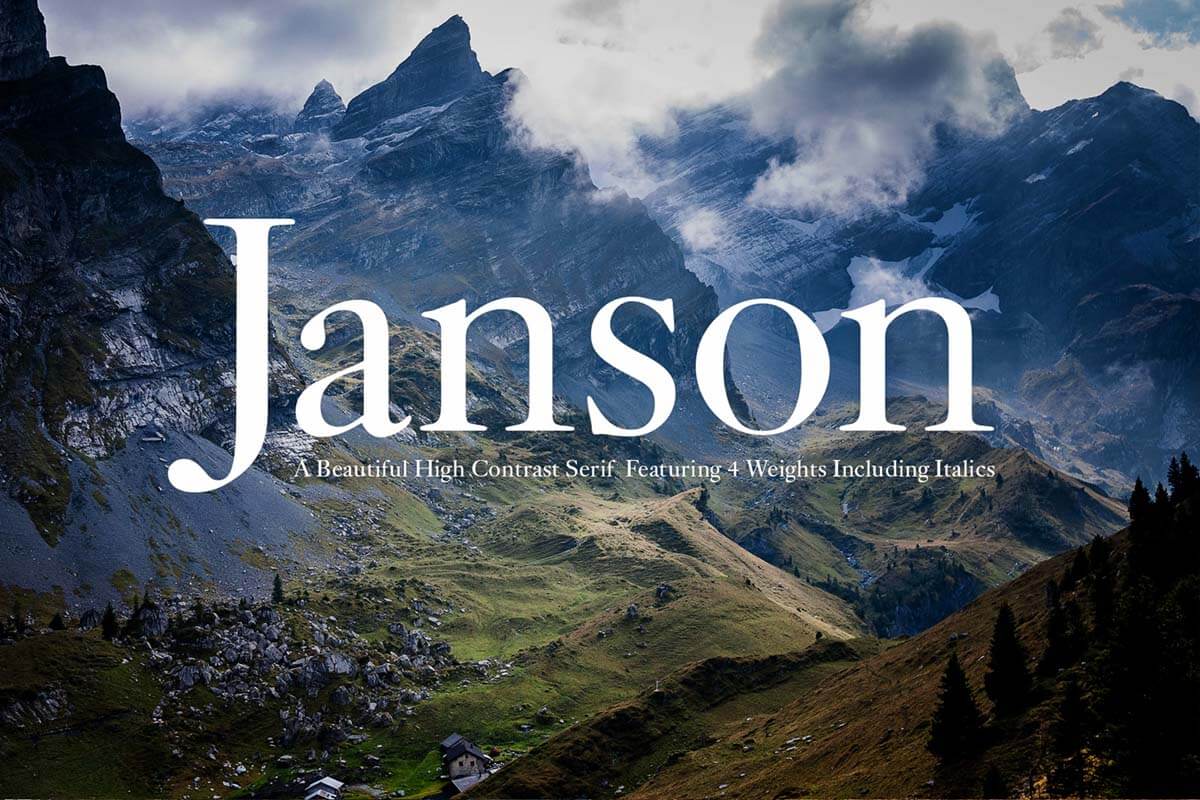
9バージョンを収録したシンプルなセリフフォント。スモールキャプスもあります。
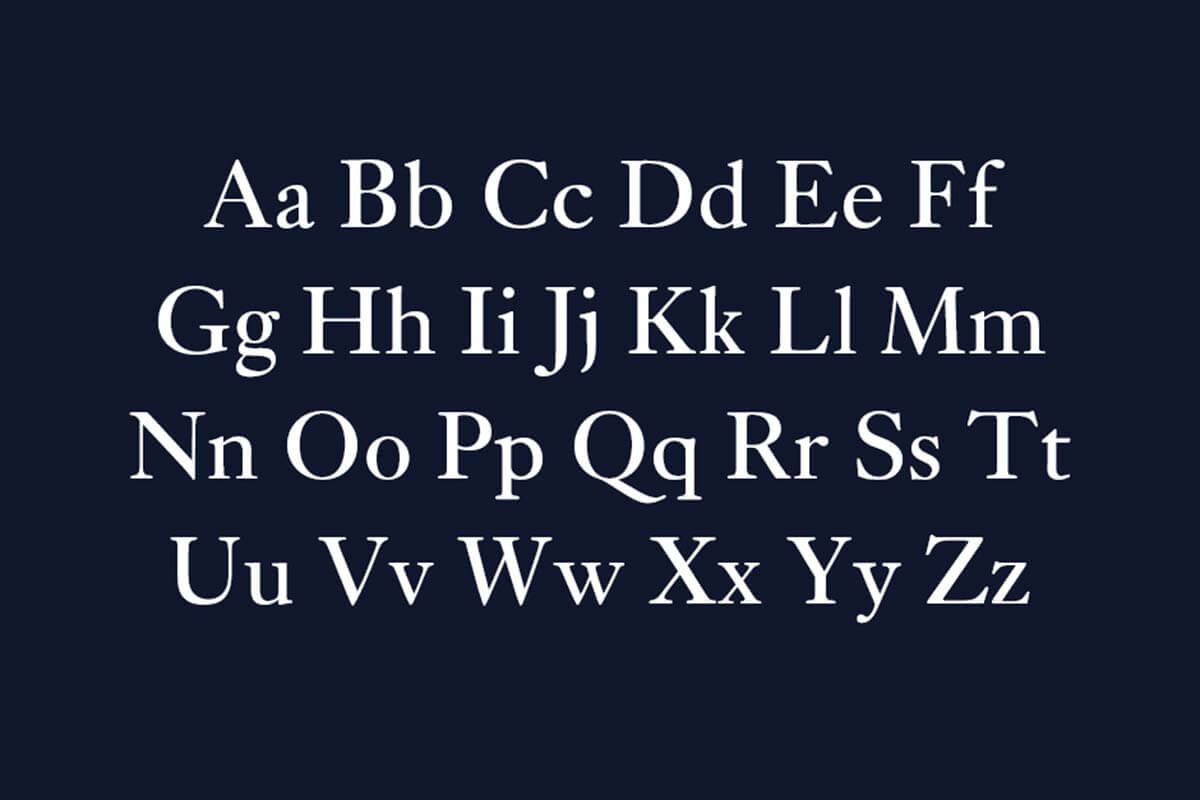
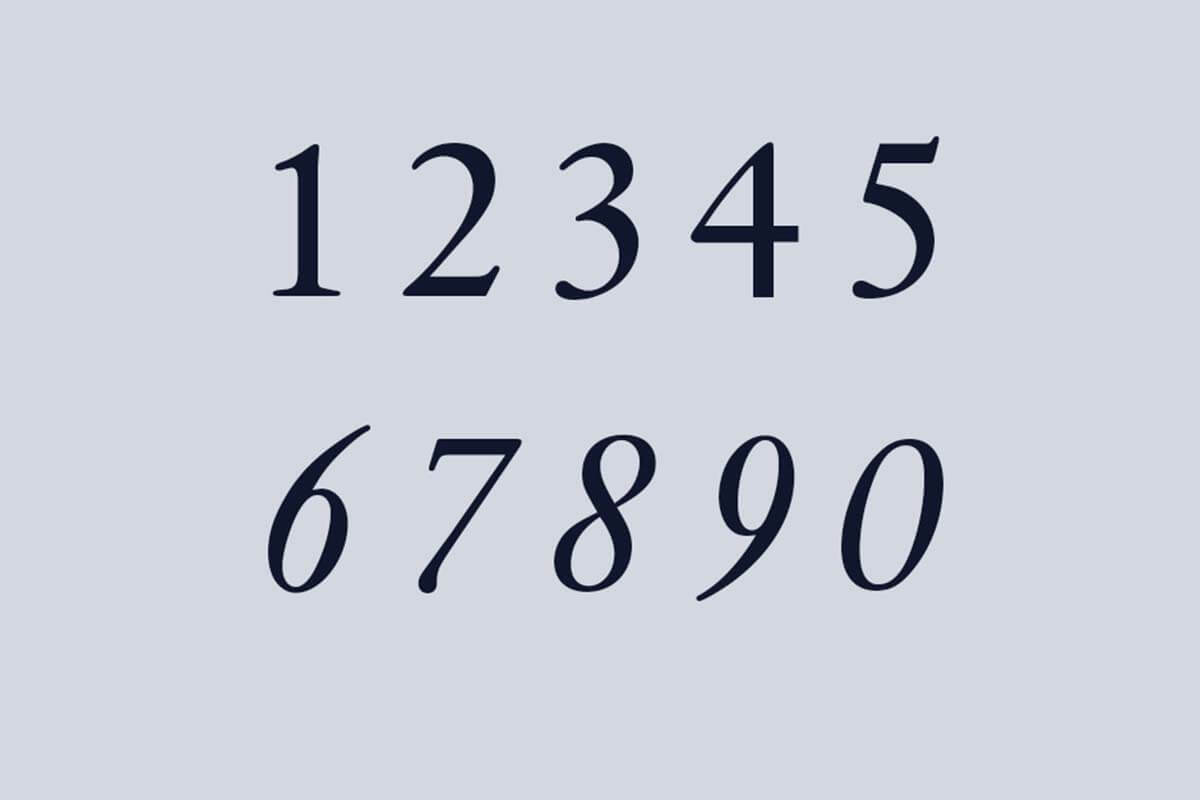
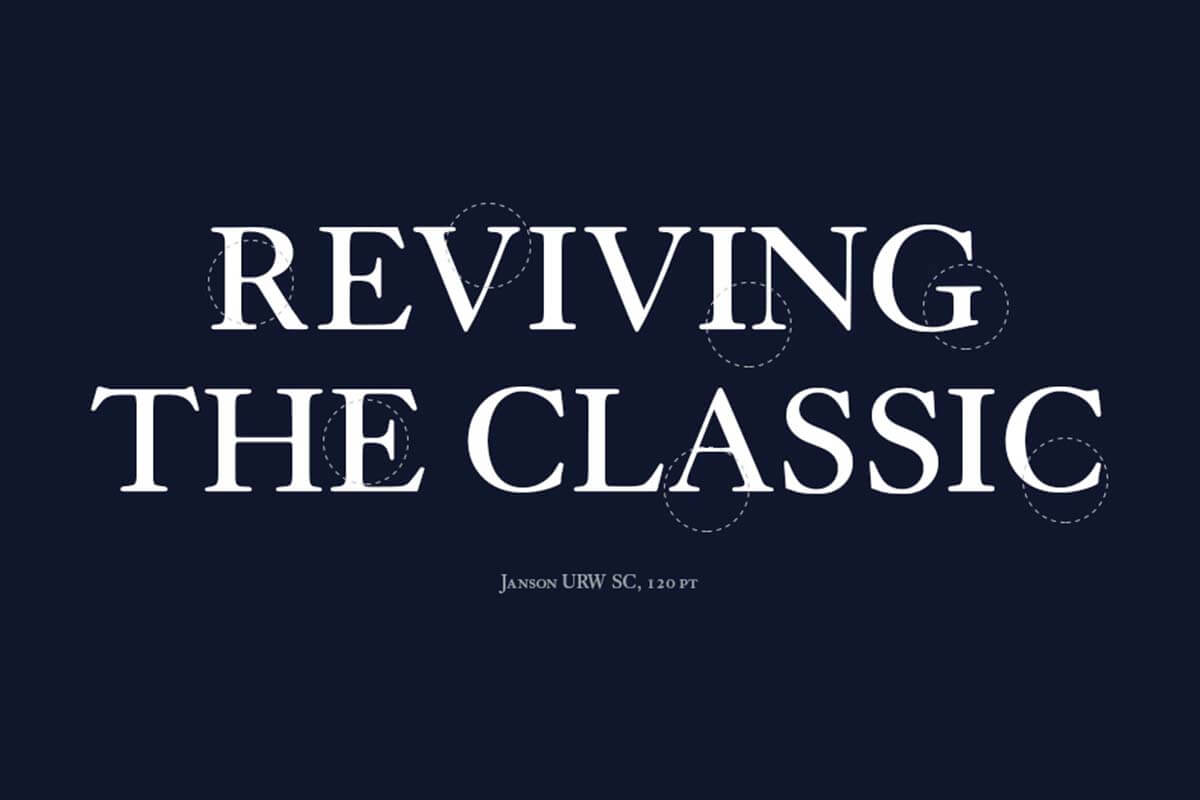
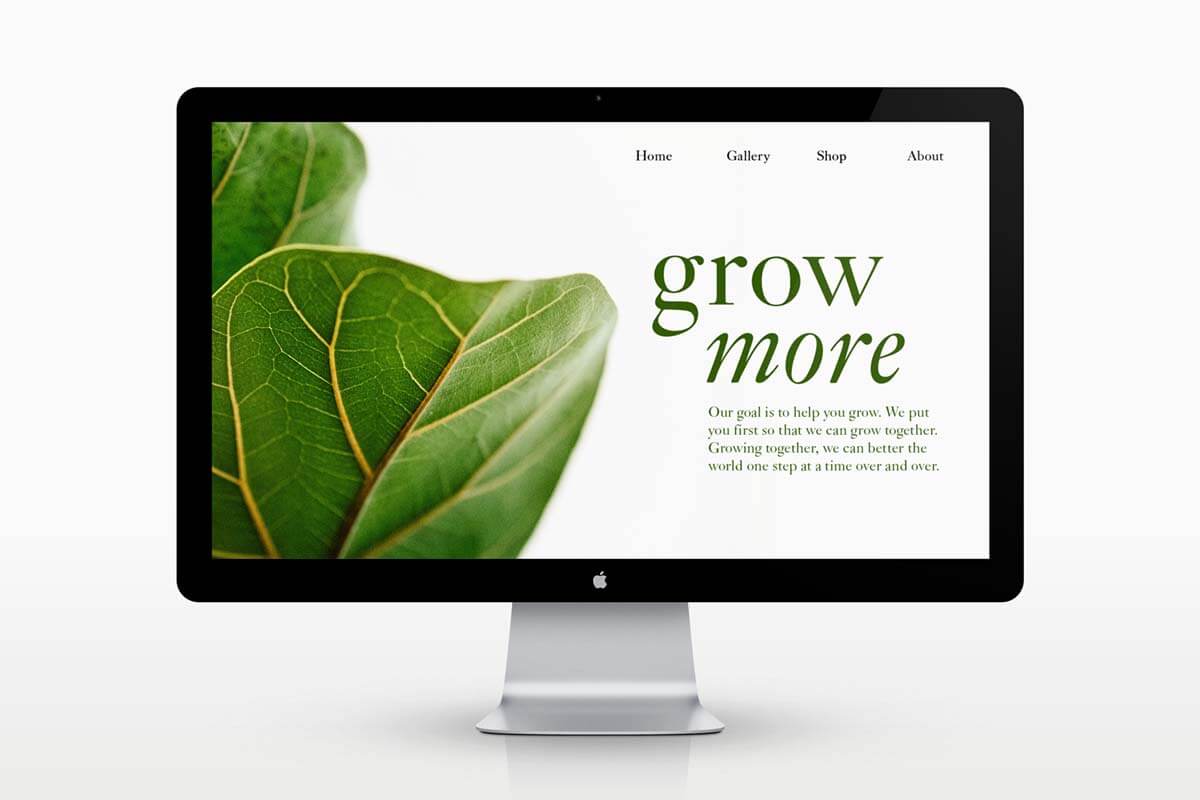
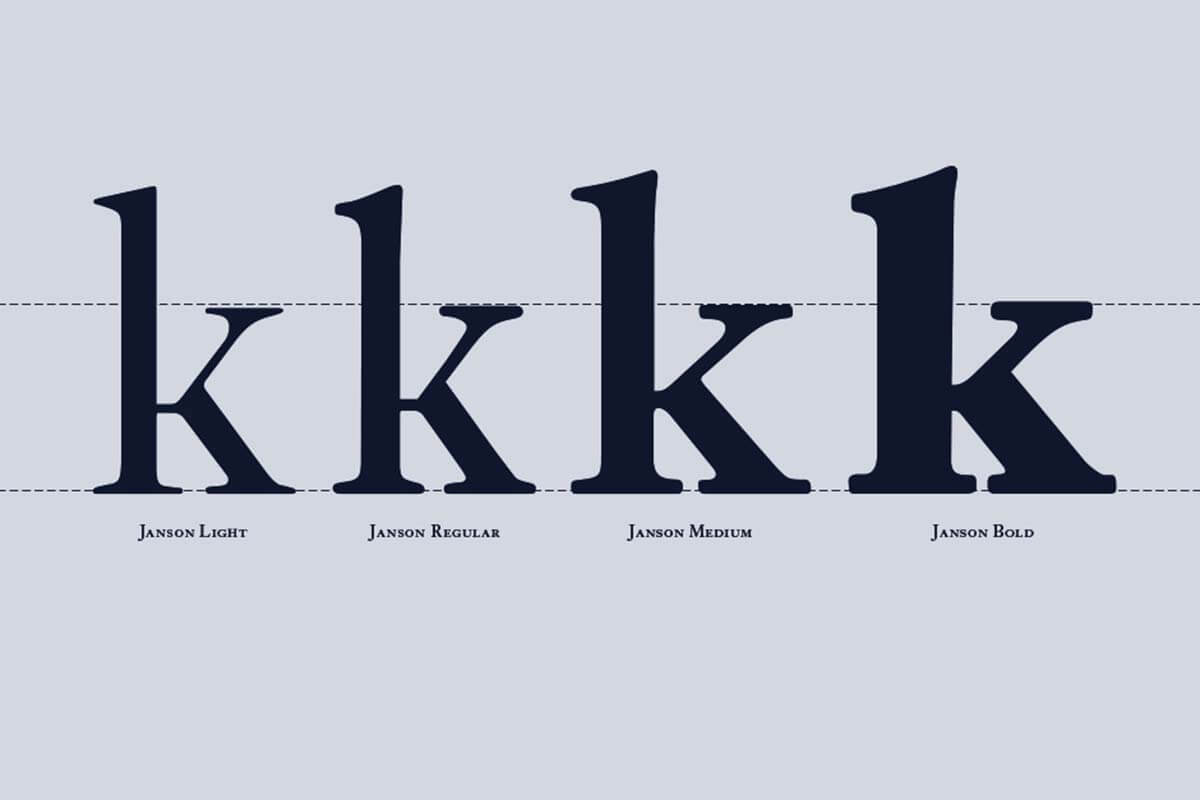
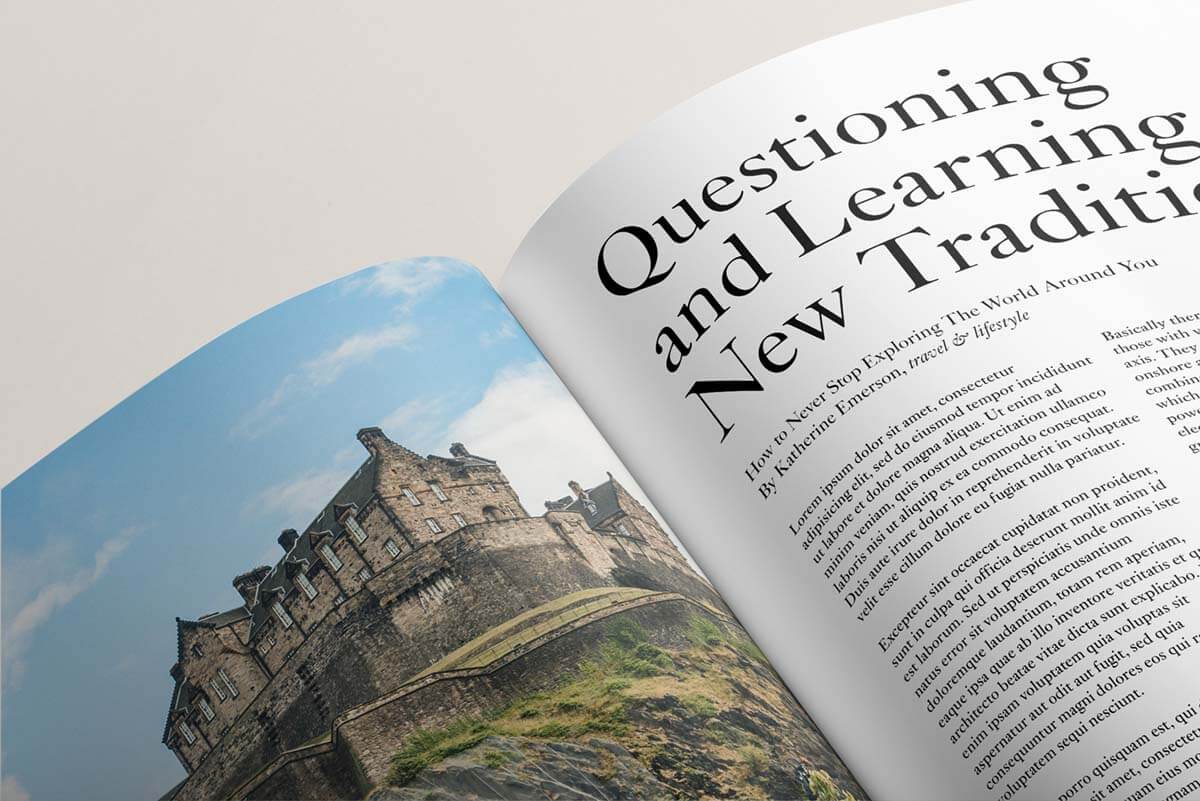
なんと90パターンの書体でデザイン自由自在:MULTIPLE
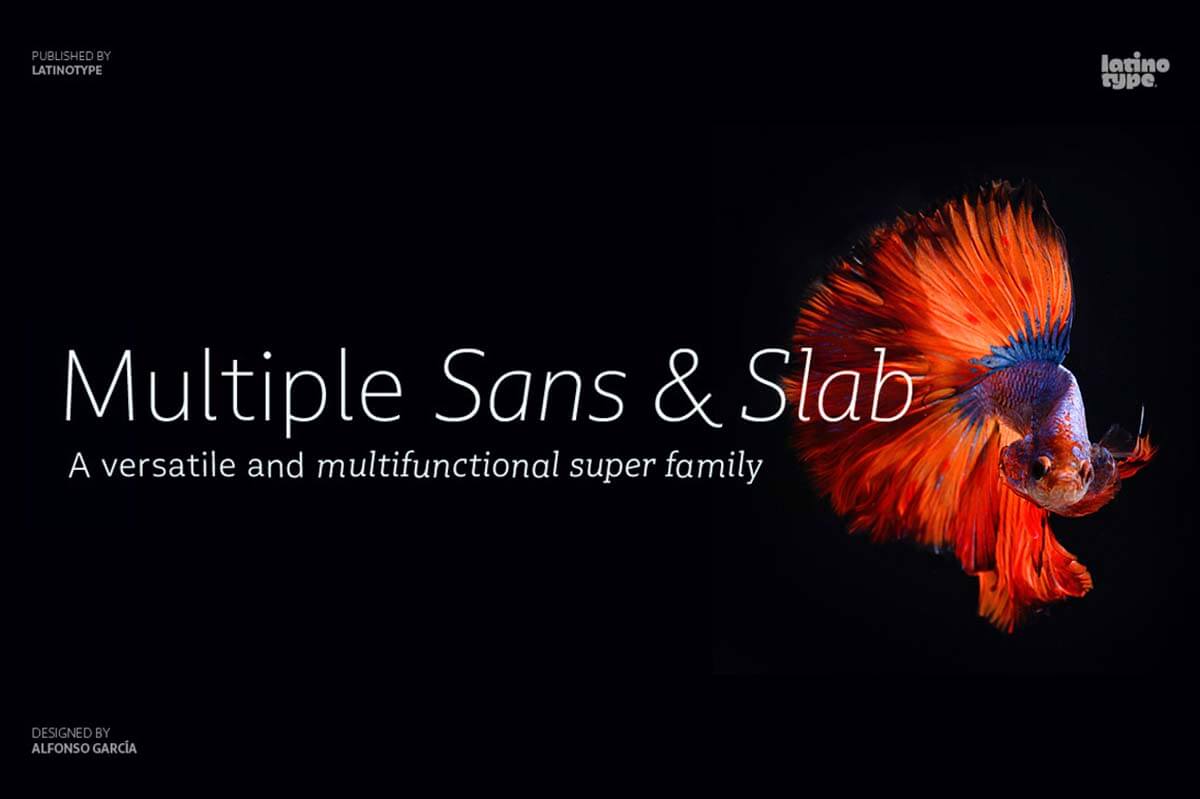
なんと90パターンものバラエティに富んだフォントファミリー。それぞれ少しずつ違うので、ぜひダウンロードして違いを比べてみてください。
このフォントさえあればデザインの仕事がはかどりそうです。